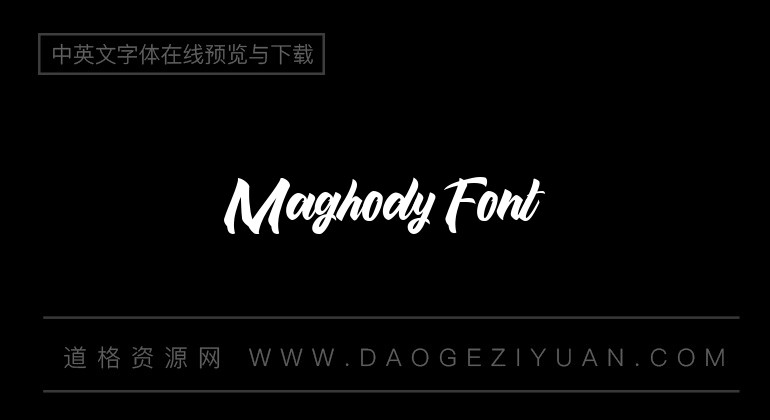
Maghody Font 是一种非常特别的手写字体,它具有非常独特的风格和特点。这种字体适用于很多场合,比如商业品牌、广告、海报、包装、标志以及印刷品等,能够给人留下深刻的印象。 Maghody Font 字体的设计灵感来源于手写风格,旨在为用户带来非常优美的视觉体验。该字体具有非常出色的可读性和易读性,因此非常适合用于任何文本或标题。 Maghody Font 字体的特点包括: 1. 独特的手写风格,非常适合创意设计和印刷品。 2. 具有出色的可读性和易读性,适用于各种大小的文本和标题。 3. 字母之间的距离非常均匀,使得整个字体看起来非常平衡和和谐。 4. 支持多种语言,包括英语、西班牙语、法语、德语、意大利语、葡萄牙语等。 Maghody Font 字体是一种非常有特色的字体,无论是商业设计还是个人项目,都可以带来非常独特的视觉效果。内容介绍
Maghody Font是一款非常不错的手写艺术字体,具有很好的视觉感,适合于文化类的宣传设计、商业类品牌的广告和产品包装设计以及个性化文字排版等较多场景。